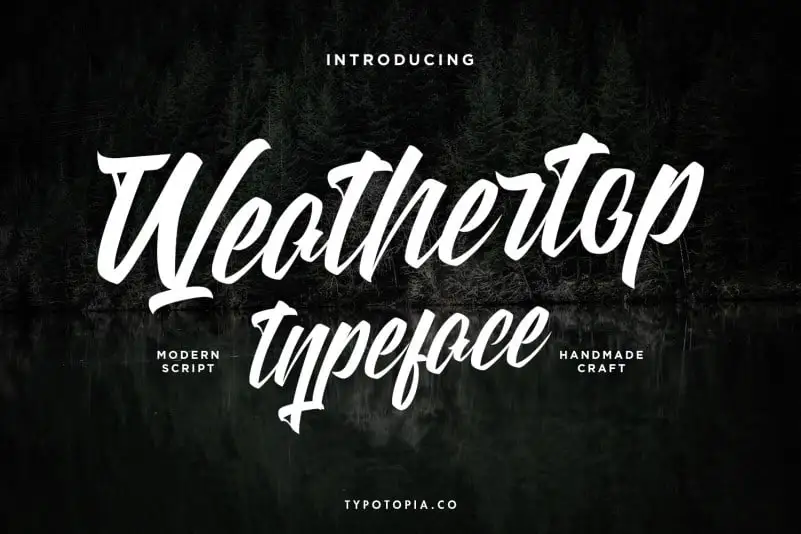
Weathertop Script Typeface – Download Grátis
Weathertop Script Typeface é uma fonte de tipografia script que traz estilo moderno à sua arte gráfica com um toque casual. Esta fonte perfeita para projetos criativos, como logos, cartões de agradecimento, convites, embalagens de produtos, cabeçalhos e logotipos, também se destaca em designs de letras, folhas de carta, panfletos, roupas e etiquetas. Ideal tanto para designers profissionais quanto amadores que buscam uma fonte de estilo script moderno e elegante. A Weathertop Script Typeface é a escolha perfeita para aqueles que desejam adicionar um toque sofisticado e criativo a seus trabalhos gráficos, seja em qualquer aplicação ou projeto da sua portfolio.